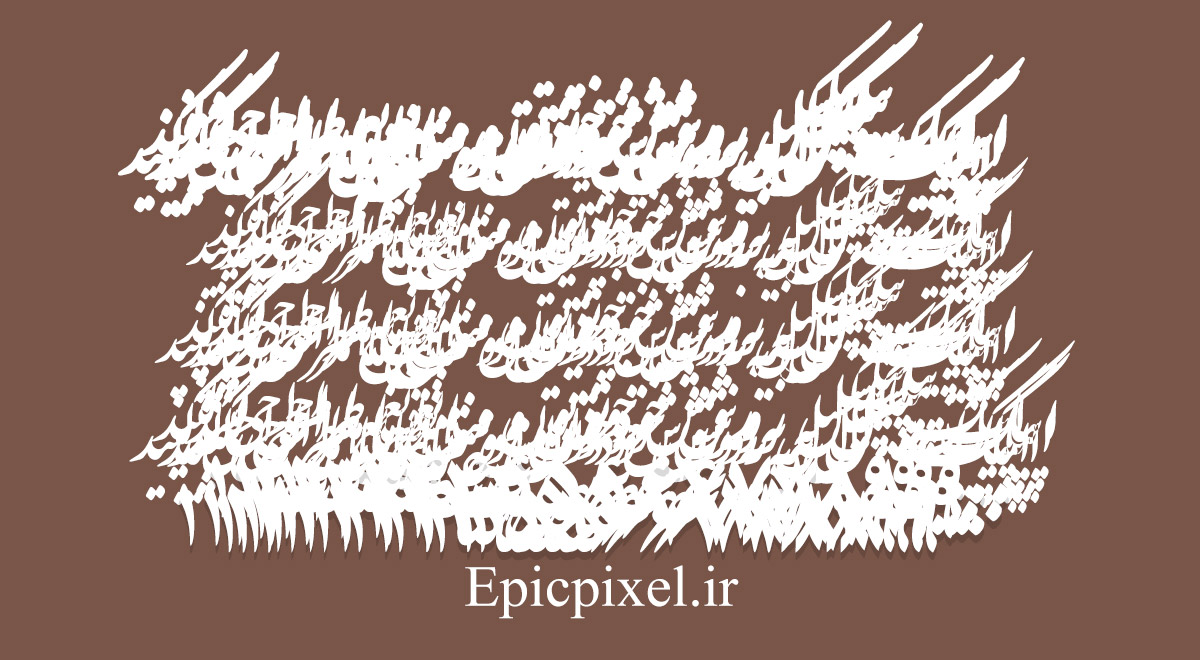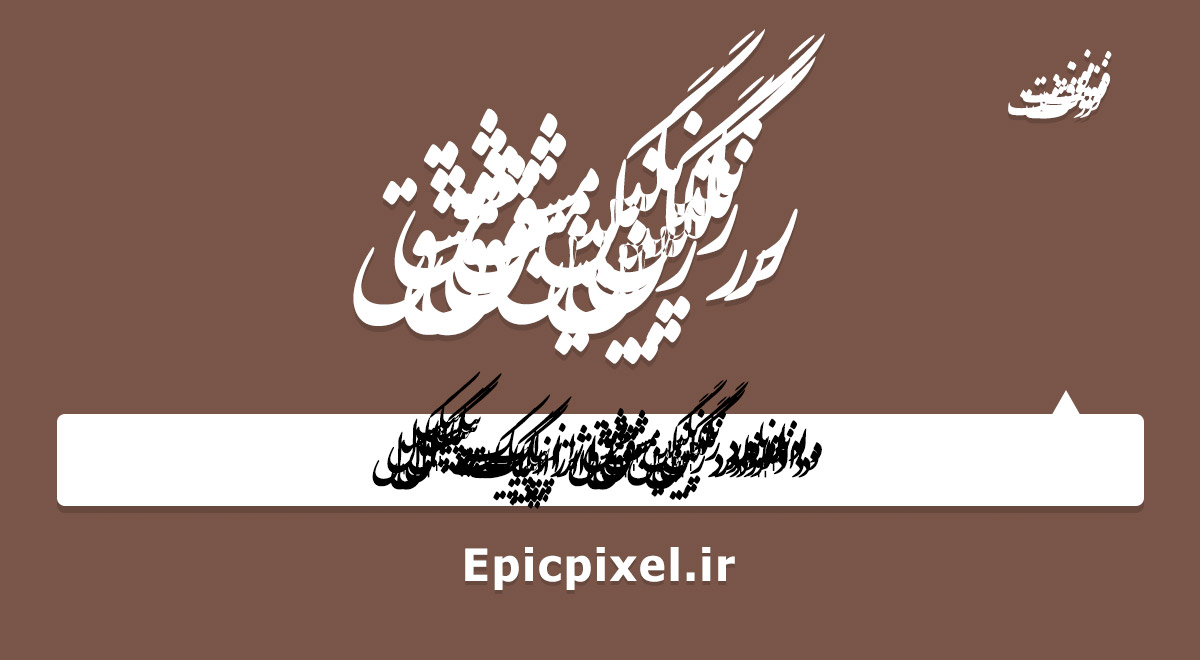
فونت رنگین مشق فارسی
فونت رنگین مشق فارسی به دلیل شباهت بسیار زیاد به خط خوشنویسی دستی و رنگارنگی حروف، انتخابی ایده آل برای طراحی های جذاب، کارت های تبریک، پوسترهای آموزشی، کتاب های کودک و نوجوان و هر کجا که نیاز به ظاهری زیبا و سنتی با لمس مدرنیته باشد، است. این فونت با ایجاد حس نوستالژی و در عین حال شادابی، توجه مخاطب را به خود جلب کرده و به متن شما عمق و زیبایی بصری می بخشد.